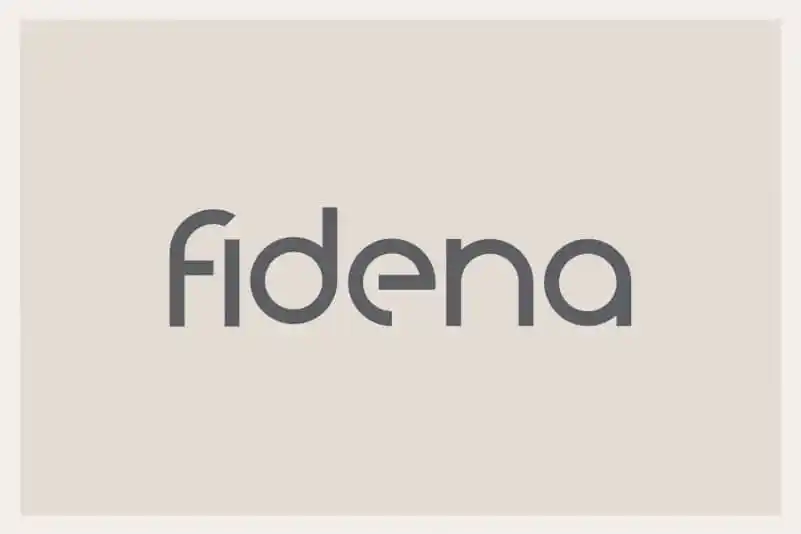
A Fidena Font é uma elegante fonte sans serif que destaca-se por sua simplicidade e estilização suave. Perfeita para diversos tipos de projetos, ela tem um design minimalista que torna-a versátil e ideal para qualquer ocasião. Com quatro pesos excepcionais – normal, esculpido, grosso e fino – a Fidena está preparada para complementar seu trabalho com serifs ou scripts sem dar uma sensação exagerada. Este é um verdadeiro conselheiro de estilo que vai se destacar em qualquer design. Descubra por si mesmo o poder desta fonte única!